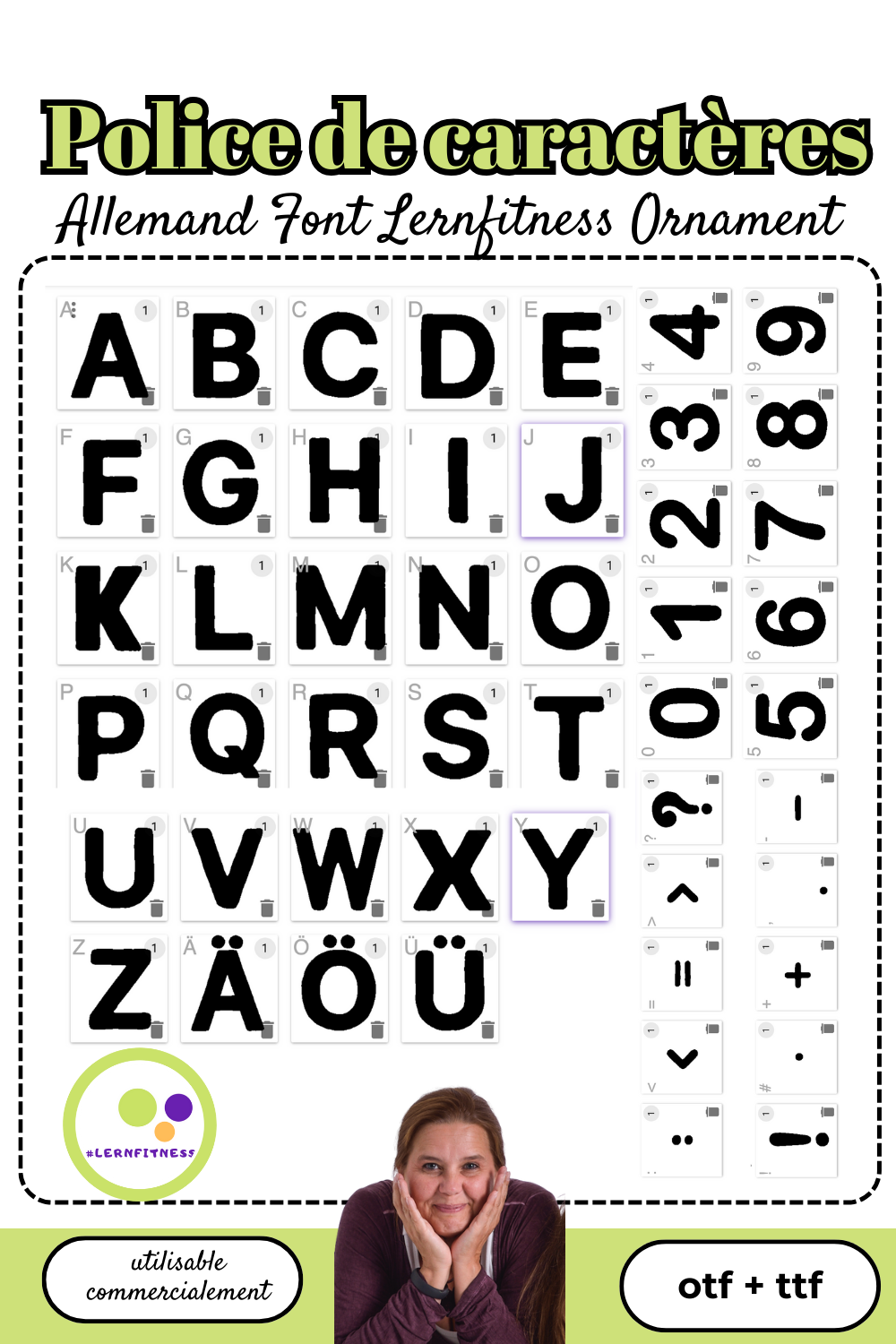
Font Lernfitness | police de caractères allemande + anglais| commerciale | police décorative
Cette police a été dessinée avec amour par mes soins. Elle est particulièrement adaptée aux titres et aux calculs simples.
Elle est composée de toutes les lettres courantes en Allemagne, y compris les trémas ä, ö, ü.
En outre, les chiffres et les signes de calcul habituels sont intégrés, comme illustré. Un véritable point de dessin se trouve sous le signe #.